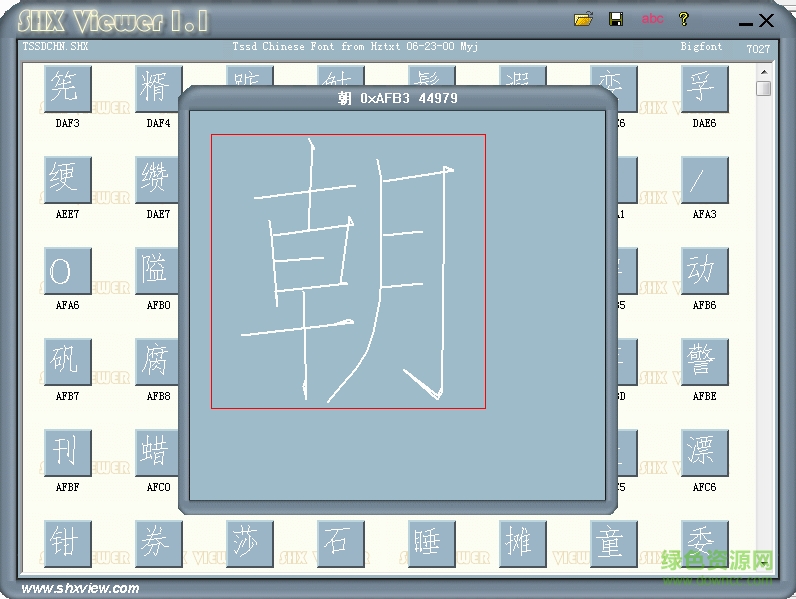
atssdchn.shx
atssdchn.shx是一款擁有7027個(gè)字符的cad字體,字跡飄逸灑脫,很有古風(fēng)韻味,字庫(kù)豐富覆蓋交廣,流暢的字形和簡(jiǎn)約的筆觸讓人很有視覺(jué)好感,綠色資源網(wǎng)歡迎大家免費(fèi)下載!
atssdchn.shx字體介紹
atssdchn.shx可能是tssdchn.shx字體被其他用戶私自修改名稱后的字體,tssdchn.shx是一款可以解決大部分鋼筋符號(hào)亂碼的autocad字體。